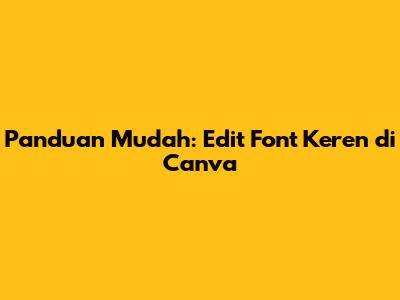
- Pilih atau Buat Desain: Pilih salah satu template yang ada atau mulai dengan kanvas kosong. Tentukan ukuran desain yang Anda inginkan (misalnya, postingan Instagram, presentasi, atau poster).
- Tambahkan Teks: Klik ikon "Teks" di sidebar sebelah kiri. Anda akan melihat beberapa pilihan: tambahkan judul, subjudul, atau teks isi.
- Pilih Font: Setelah menambahkan kotak teks, klik di dalamnya untuk mulai mengetik. Di toolbar yang muncul di atas, Anda akan melihat dropdown menu yang menampilkan daftar font yang tersedia. Klik menu tersebut untuk memilih font yang Anda suka.
- Edit Teks: Setelah memilih font, Anda bisa mulai mengedit teks sesuai keinginan Anda. Ubah isi teks, ukuran font, warna, gaya (tebal, miring, garis bawah), dan perataan (kiri, tengah, kanan, rata kiri-kanan).
- Pertimbangkan Tujuan Desain: Apa pesan yang ingin Anda sampaikan? Apakah Anda ingin terlihat formal, kasual, modern, atau klasik? Pilihlah font yang sesuai dengan tujuan desain Anda.
- Cocokkan dengan Gaya Desain: Jika desain Anda minimalis, pilih font yang sederhana dan bersih. Jika desain Anda berwarna-warni dan ceria, Anda bisa memilih font yang lebih berani dan unik.
- Perhatikan Keterbacaan: Pastikan font yang Anda pilih mudah dibaca, terutama untuk teks berukuran kecil. Hindari font yang terlalu rumit atau berlebihan.
- Gunakan Kombinasi Font yang Tepat: Jangan gunakan terlalu banyak font dalam satu desain. Gunakan maksimal dua atau tiga font yang berbeda untuk judul, subjudul, dan isi teks. Pastikan font-font tersebut saling melengkapi.
- Coba-coba dan Eksplorasi: Jangan takut untuk mencoba berbagai font. Canva menyediakan banyak pilihan font yang bisa Anda eksplorasi. Lihat bagaimana font terlihat dalam berbagai kombinasi dan ukuran.
- Ukuran Font: Di toolbar, Anda bisa mengatur ukuran font dengan mengklik ikon ukuran font dan memilih ukuran yang Anda inginkan. Anda juga bisa mengubah ukuran font dengan menarik kotak teks.
- Warna Font: Klik ikon warna di toolbar untuk mengubah warna font. Anda bisa memilih warna dari palet warna yang tersedia, menggunakan kode warna, atau memilih warna dari foto yang Anda unggah.
- Gaya Font: Anda bisa membuat teks menjadi tebal (Bold), miring (Italic), atau menggarisbawahi (Underline) dengan mengklik ikon B, I, atau U di toolbar.
- Perataan Teks: Anda bisa meratakan teks ke kiri, tengah, kanan, atau rata kiri-kanan dengan mengklik ikon perataan di toolbar.
- Efek Teks: Anda bisa menambahkan efek bayangan, efek timbul, efek melengkung, dan berbagai efek lainnya. Eksplorasi berbagai efek untuk menemukan yang paling cocok dengan desain Anda.
- Animasi Teks: Jika Anda membuat desain untuk video atau presentasi, Anda bisa menambahkan animasi pada teks Anda. Canva menawarkan berbagai jenis animasi, mulai dari animasi masuk, animasi keluar, hingga animasi loop. Pilih animasi yang sesuai dengan gaya desain Anda.
- Jarak Antar Huruf: Anda bisa mengatur jarak antar huruf dengan mengklik ikon jarak antar huruf di toolbar. Sesuaikan jarak antar huruf untuk membuat teks terlihat lebih rapi dan mudah dibaca.
- Jarak Antar Baris: Anda bisa mengatur jarak antar baris teks dengan mengklik ikon jarak antar baris di toolbar. Sesuaikan jarak antar baris untuk membuat teks terlihat lebih nyaman untuk dibaca.
Canva adalah platform desain grafis yang sangat populer, bahkan buat pemula sekalipun. Kemudahannya dalam penggunaan dan pilihan desain yang beragam membuat banyak orang jatuh cinta. Salah satu aspek penting dalam desain adalah tipografi, atau seni mengatur font (huruf). Di Canva, Anda bisa berkreasi dengan font untuk menghasilkan desain yang menarik perhatian. Mari kita bahas cara mengedit font di Canva, mulai dari dasar-dasar hingga tips yang lebih lanjut.
Memulai: Akses dan Antarmuka Canva
Guys, sebelum kita mulai, pastikan Anda sudah memiliki akun Canva dan sudah login. Jika belum, daftar dulu, ya! Gampang banget kok. Setelah masuk, Anda akan melihat antarmuka Canva yang ramah pengguna. Di sini, Anda bisa memilih berbagai template desain yang sudah tersedia, atau membuat desain baru dari kanvas kosong. Nah, untuk memulai mengedit font di Canva, ikuti langkah-langkah berikut:
Gampang kan? Dengan langkah-langkah dasar ini, Anda sudah bisa memulai petualangan mengedit font di Canva. Tapi, tunggu dulu, masih banyak lagi yang bisa Anda lakukan!
Memilih Font yang Tepat untuk Desain Anda
Guys, pemilihan font yang tepat sangat penting untuk kesuksesan desain Anda. Font bisa menyampaikan pesan, membangun identitas merek, dan menarik perhatian. Berikut adalah beberapa tips dalam memilih font:
Dengan memperhatikan tips ini, Anda bisa memilih font yang tepat untuk desain Anda dan membuatnya semakin menarik.
Kustomisasi Font Lanjutan di Canva
Oke, guys, setelah Anda menguasai dasar-dasar dan memilih font yang tepat, saatnya untuk meningkatkan keterampilan mengedit font Anda dengan kustomisasi yang lebih lanjut. Canva menawarkan berbagai opsi untuk membuat teks Anda semakin menarik dan unik.